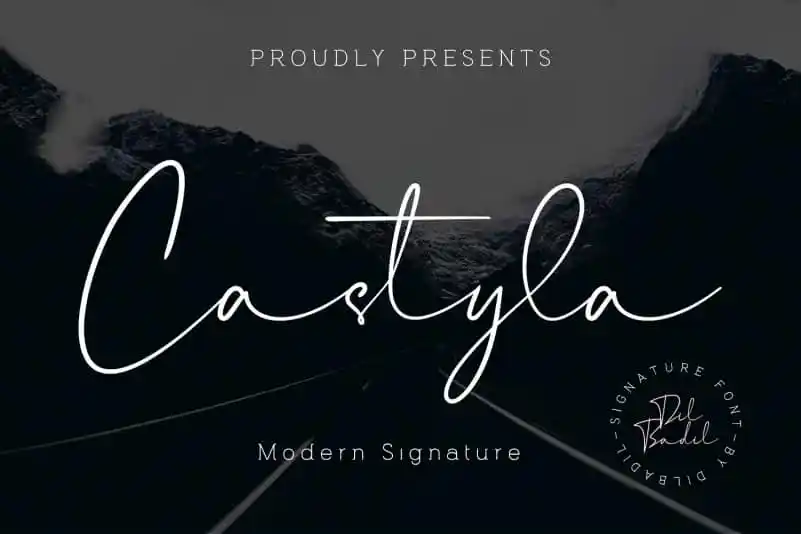
Aqui está uma descrição do Castyla Signature Font para sua página de download, mantendo a essência do texto original: Castyla é um novo conjunto de letras elegantes que oferece um toque único e sofisticado. Este font é especialmente projetado como ‘Signature’, trazendo à memória o jeito amigável e familiar da escrita à mão. O Castyla Signature não apenas serve bem para as necessidades do seu negócio, como logotipos, cartões de visita ou convites de casamento, mas também se destaca quando você deseja transmitir um sentimento pessoal através de uma frase ou quote. Inspirado no estilo natural das escritas à mão, este font é perfeito para aqueles que procuram dar a sua marca um toque personalizado e profissional.
Designer: dilbadil